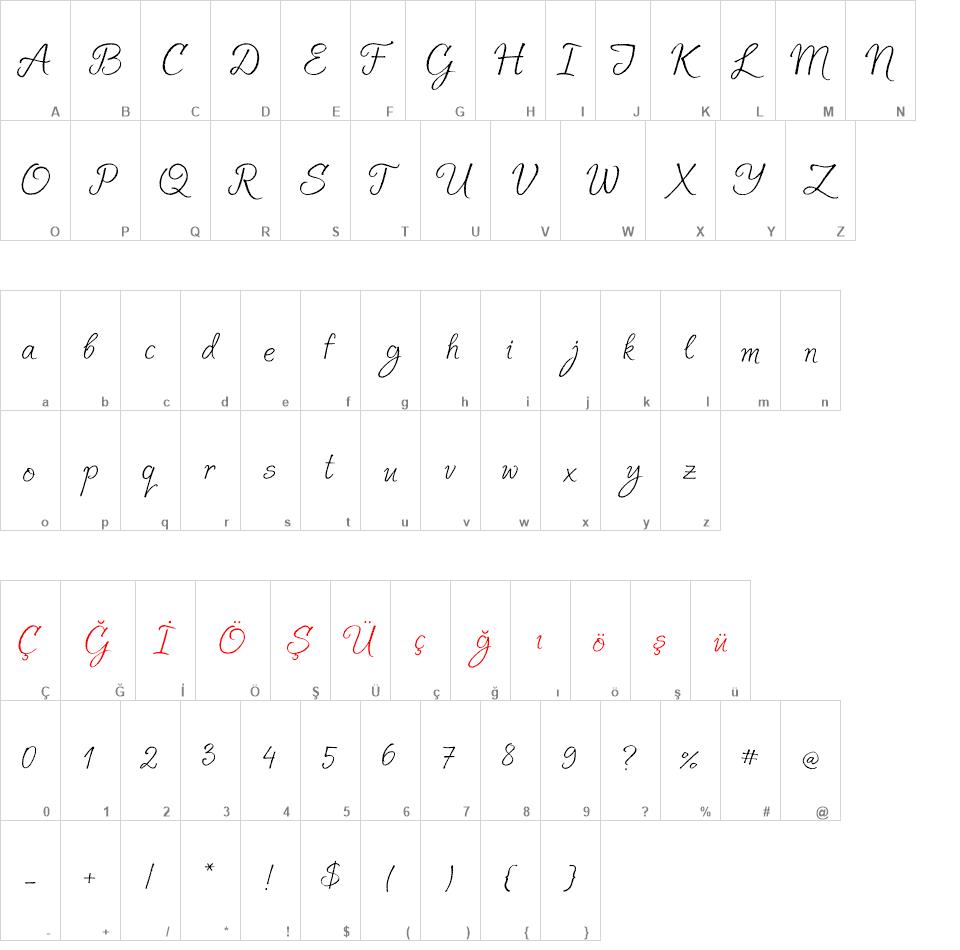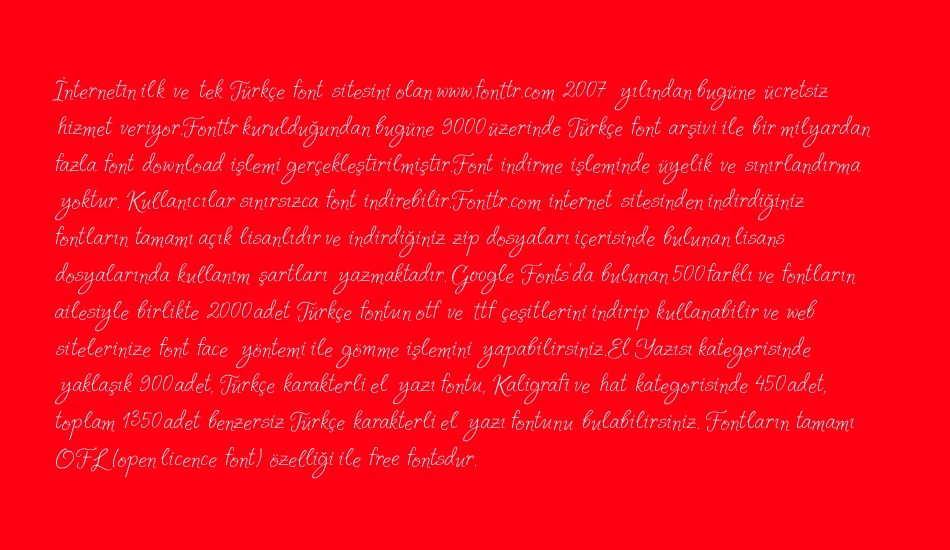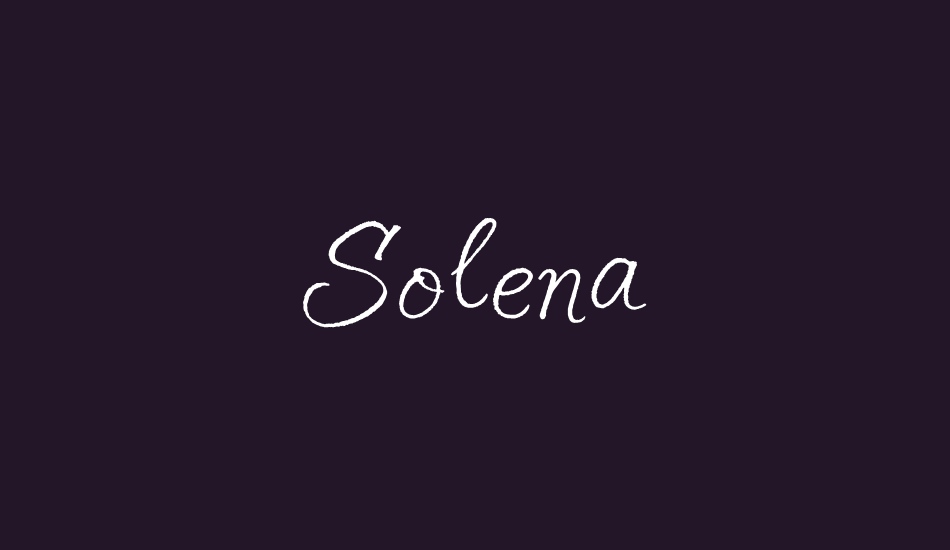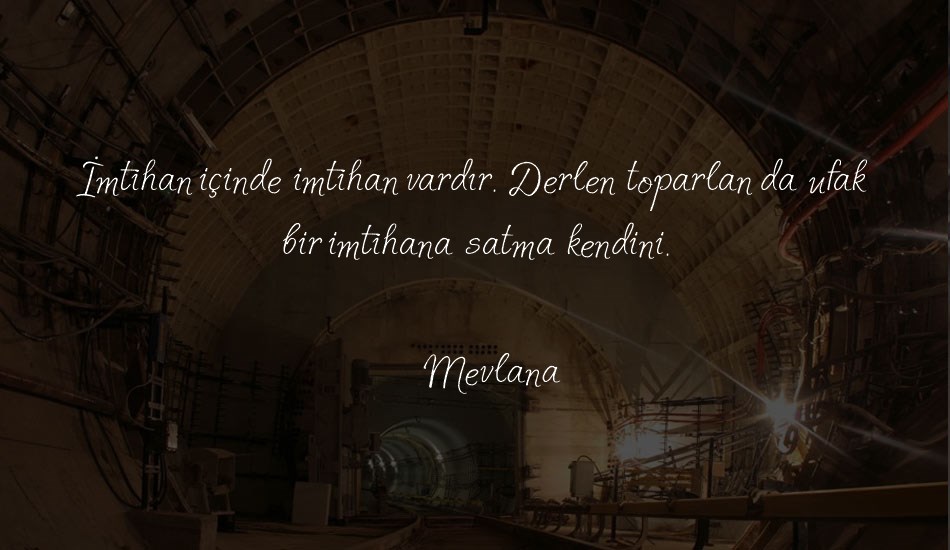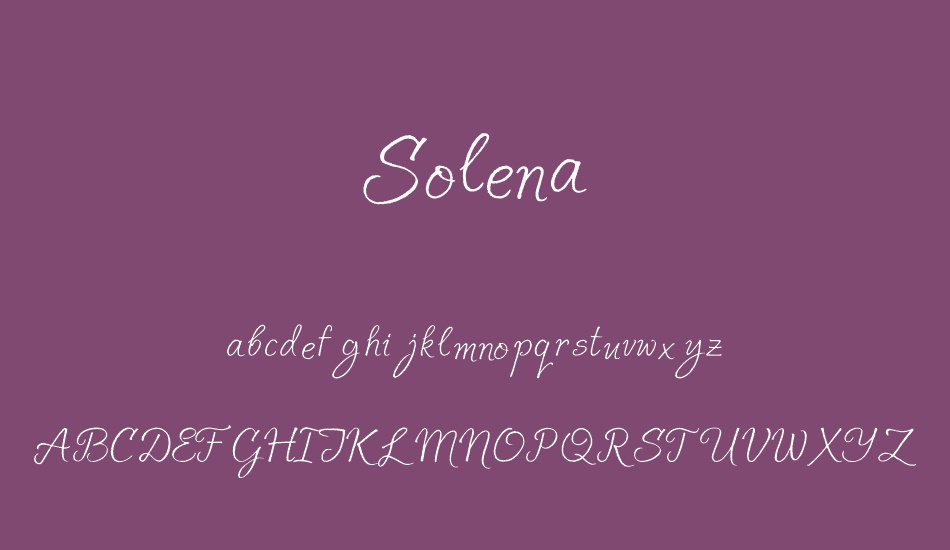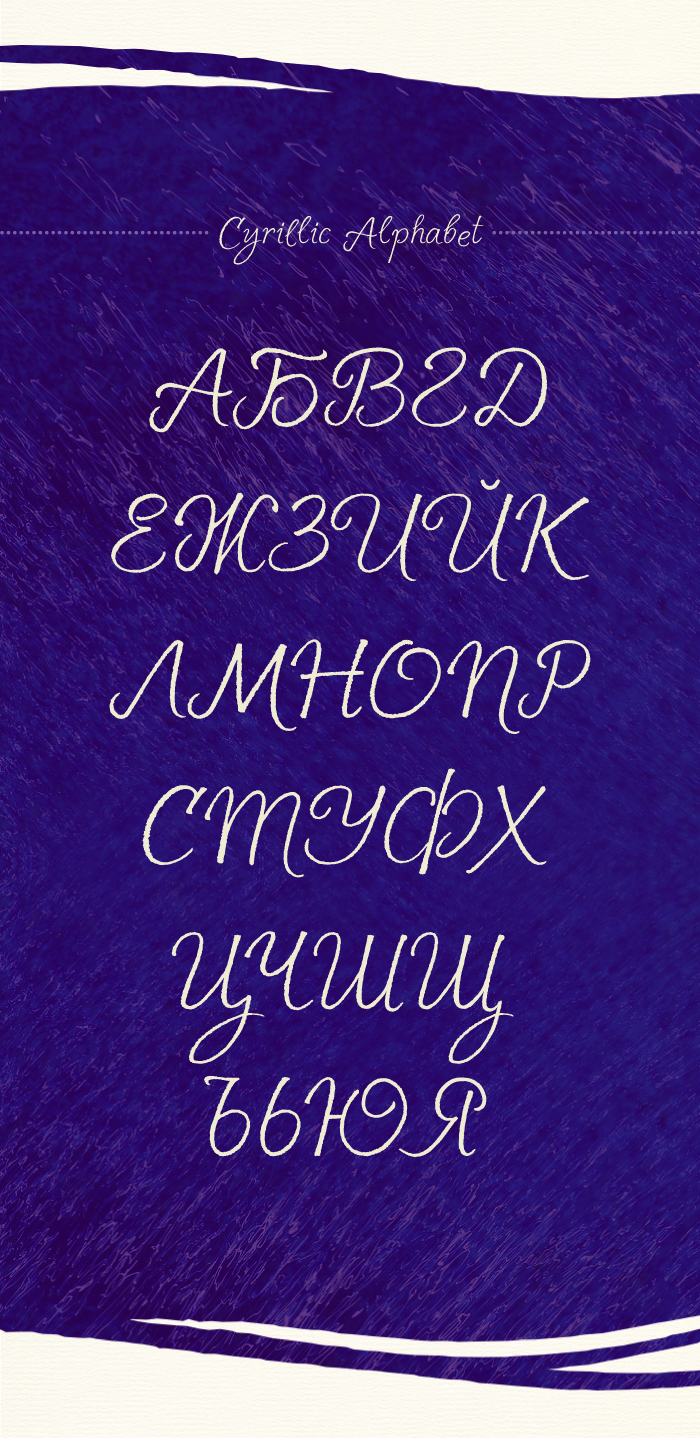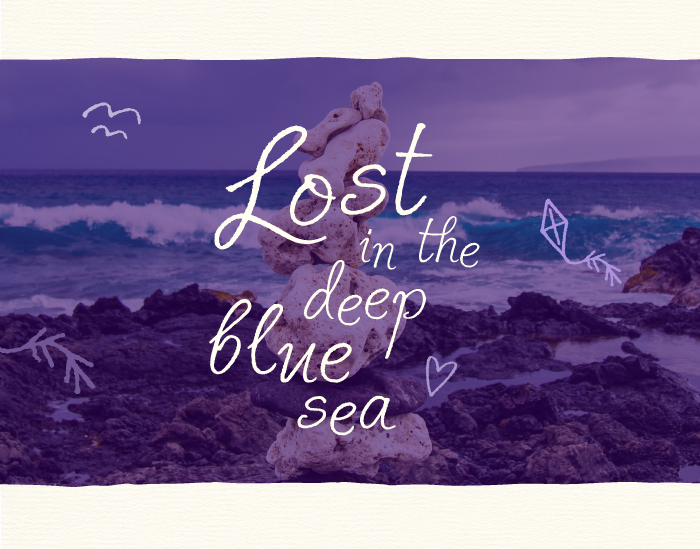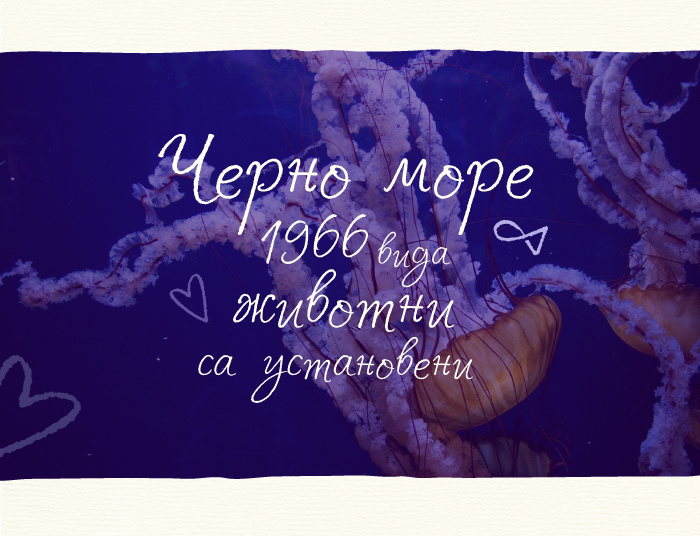
Solena font
Solena el yazısı yazı tipidir. Dokulu kağıda bir kalem kullanılarak yazılmış hissi verir.
Harfler el yazısı özgürlüğünü taban üzerinde düzensiz yerleştirilir.
Yazı tipi üslup alternatifleri ve bazı benzersiz kartpostal, davetiye, afiş veya ambalajı yapmak için yaratıcılığınızı yatkın bir OpenType özelliği olarak vardır. Varsayılan olarak iyi görünümlü harf kombinasyonları sağlamak için bitişik harfler bir sürü içerir. Solena ezbere yapılan özel ürünler desteklemek için tasarlanmıştır.